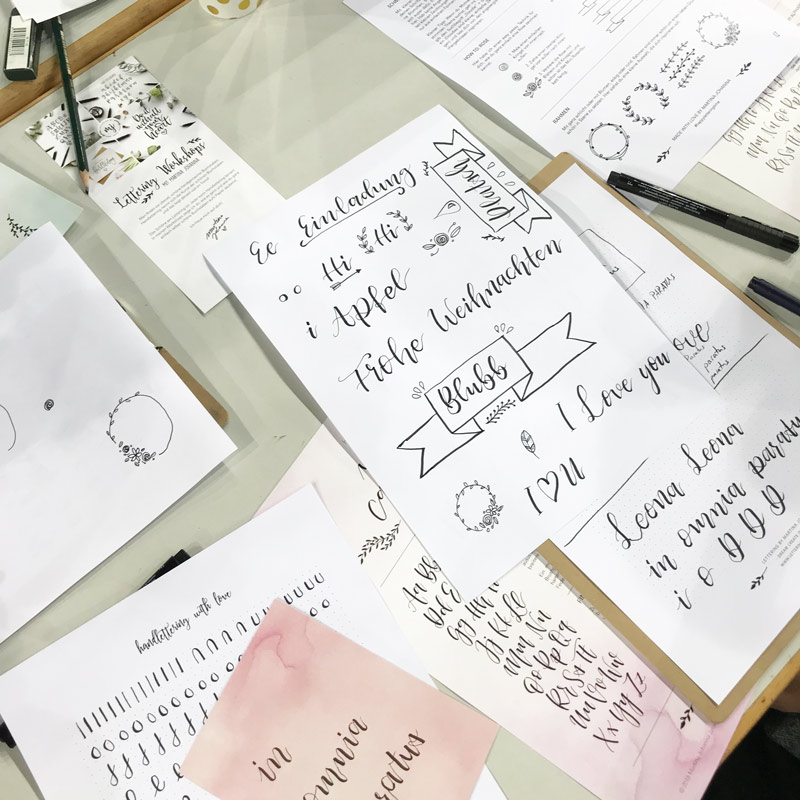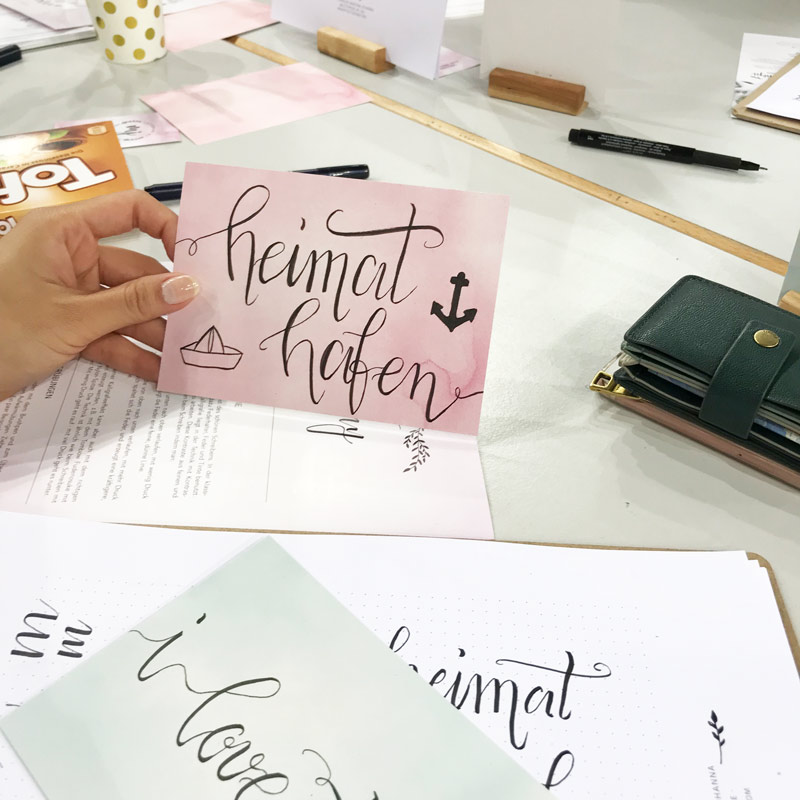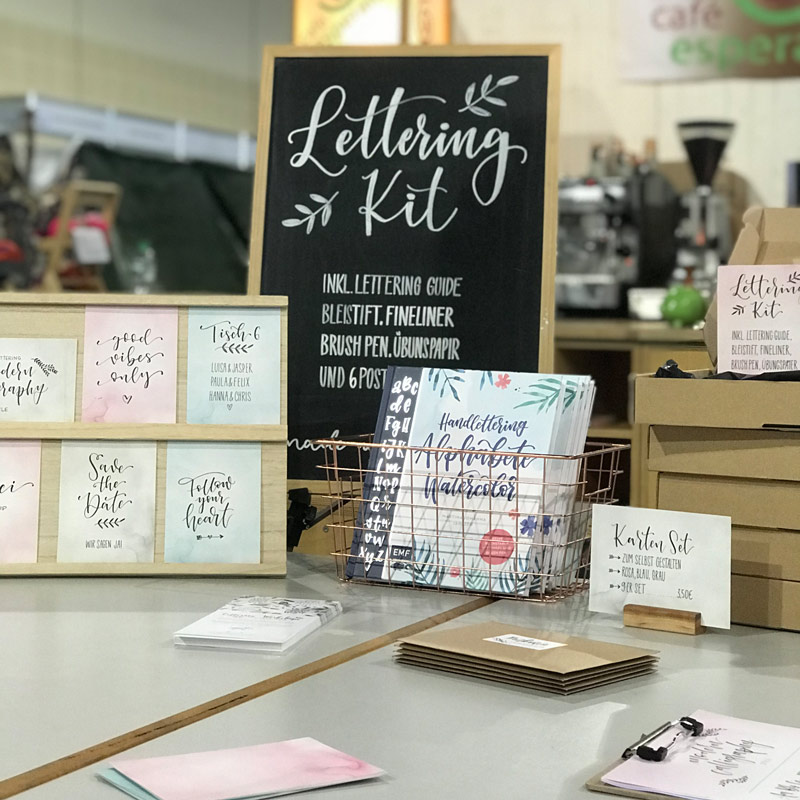
Lettering Workbook - Der Lettering Workshop für zuhause
Workbook – Moderne Kalligrafie mit dem Brushpen (Ausverkauft)
Brushlettering Workbook von Martina Johanna - Der Lettering Workshop für zuhause
Lettering by Martina Johanna - Workbook Moderne Kalligrafie mit dem Brushpen Brushlettering Workbook von A-Z
Workbook - Brush Lettering Workshop für zuhause
Der Lettering Workshop für zuhause
Das Workbook enthält auf 24 Seiten Anleitungen, Buchstabenvorlagen sowie Tipps und Tricks rund um das Thema „Moderne Kalligrafie mit dem Brushpen“.
Mein Stand auf der Kreatibzeit in den Messehallen Bremen zum Thema Brushlettering, Moderne Calligraphy
Kreativzeit – Rückblick und Materialliste
Schön war es auf der Kreativzeit in den Messehallen Bremen. Drei Tage lang durfte ich dort kleine Schnupperkurse zum Thema „Brushlettering im modernen Kalligrafie Stil“ geben. Es war unglaublich aufregend und schön, so viele Menschen zu treffen, die Lust auf schöne Buchstaben haben getreu dem Motto: Endlich wieder schön schreiben!
Lettering Workshop auf der Trauzeit und Kreativzeit in Bremen
Hello Hanselife – Kreativzeit in Bremen
Lettering "Merci" Brushlettering Modern Calligraphy
Brushlettering Modern Calligraphy Style
Auf dem Besondersmarkt Hamburg durfte ich einen kleinen Schnupperworkshop zum Thema Handlettering geben. Das Thema, das ich vorbereitet hatte lautete:
BRUSHLETTERING  MODERN CALLIGRAPHY STYLE und es war wunderbar zu sehen, wieviele tolle Buchstaben aufs Papier gezaubert wurden. Danke an alle die mitgemacht haben – ihr wart wunderbar! Und Danke auch an die liebe Corinna von cosabe-artwork, für die fantastische Unterstützung!
Besonders Hamburg // Design und Foodmarkt mit Lettering Schnupperkurs u.v.m // 8.April 2018
Lettering Schnupperkurs in Hamburg
ein Lettering mit "Ahoi Hamburg", designed by Martina Johanna, Handlettering Künstlerin aus Bremen, modern Calligraphy Auf dem Besonders Markt in Hamburg wird es dieses Jahr besondersschön und besonderslecker. Es sind wie immer tolle Aussteller dabei und wie ich gehört habe, wird es dort auch kulinarische Köstlichkeiten geben. Ich weiß gar nicht, worauf ich mich am meisten freue ;D
2016 habe ich übrigens mein Debüt als Handlettering-Dozentin auf dem besondersschön Markt in Hamburg gegeben und ich freue mich besonders doll, dass ich dieses Jahr wieder dabei sein darf ♥️
Watercolor Lettering Workshop in Hamburg - presented by Nadja Dünnwald Events
Lettering Workshop in Hamburg – presented by Nadja Dünnwald Events
Im Oktober 2017 bekam ich eine Mail von Nadja Dünnwald. In dieser Mail erzählte sie mir von ihren Plänen, einen Lettering Workshop in Hamburg zu veranstalten und fragte mich, ob ich Lust hätte, diesen als Dozentin zu begleiten. Ich hab „Ja“ gesagt und aus einem Lettering Workshop in Hamburg wurden direkt zwei.
Hand Lettering Workshop bei FoBi-X
Am Samstag den 20.Mai 2017 fand mein erster Lettering Workshop in der FoBi-X Bilderwerkstatt in Bremen statt. Mit Bleistift & Radiergummi, Finelinern und Filzstiften wurde gelettert, gelettert und gelettert. Ich bin immer noch ganz begeistert von den talentierten und fleißigen Teilnehmerinnen ? Im Juni wird es weitere Workshops mit mir in der FoBi-X Bilderwerkstatt geben. Leider sind die auch schon ausgebucht, aber weitere Workshops sind in Planung und werden ganz bald veröffentlicht. Wenn ihr keinen Termin verpassen möchtet, meldet euch zum Newsletter an: NEWSLETTER